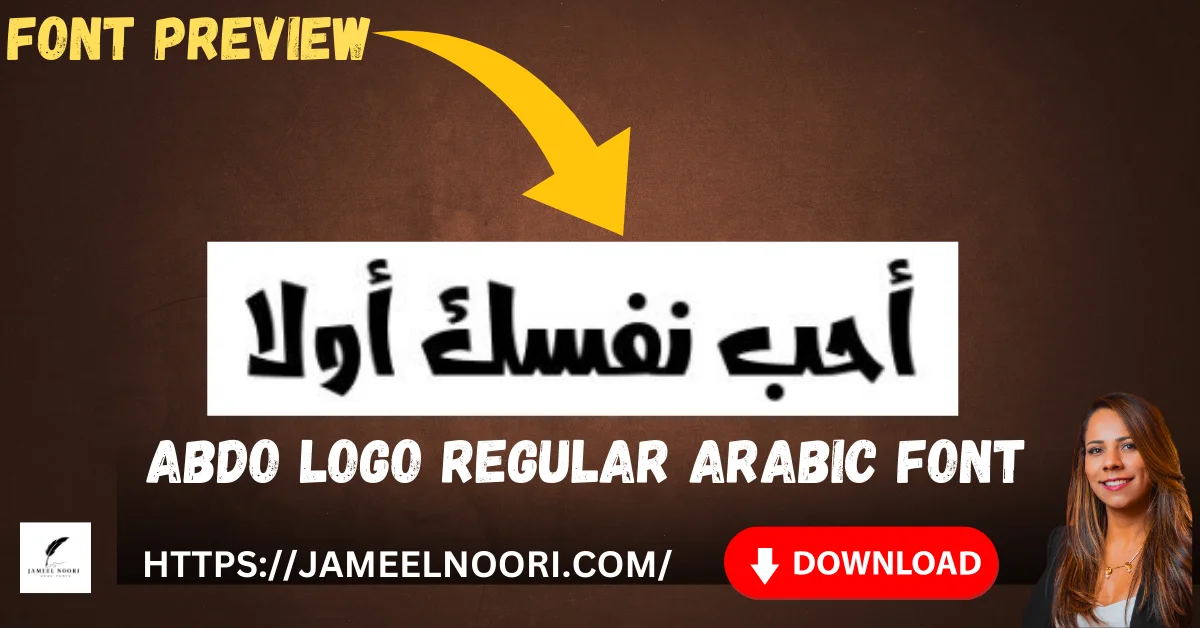
Abdo Logo Regular Arabic Font – Modern & Professional Arabic Typeface For Designers (Best & Latest Choice)
Abdo Logo Regular Arabic Font aik modern aur professional Arabic typeface hai jo specially logo design, branding, aur creative projects ke liye use hota hai. Ye font worldwide designers ke darmiyan bohat popular hai kyun ke iski clean calligraphy aur balanced letter spacing har design ko premium look deti hai. Is article me hum apko is font ke bare me complete information dy gy taki aap bina time waste kiye is font ka best use kar saken.
Key Features of Abdo Logo Regular Arabic Font
Abdo Logo Regular Arabic Font ke kuch powerful features isay market ka best arabic font banate hain:
• Clean aur modern Arabic calligraphy
• Logo aur branding ke liye perfect
• High readability on screen aur print
What Is Abdo Logo Regular Arabic Font and Why It Is the Best Choice
Is font ka structure simple magar classy hai, jo Urdu fonts aur Arabic fonts ke users dono ke liye easy readability provide karta hai. Lahore, Karachi aur dusray shehron ke designers isay logos, posters aur digital branding me frequently use karte hain.
Best Uses of Abdo Logo Regular Arabic Font Worldwide
Abdo Logo Regular Arabic Font multiple creative fields me use hota hai, jaise:
• Logo design & branding
• Social media graphics
• Website headers
• Posters & banners
• Islamic content & calligraphy
Pakistan ke ilawa Middle East aur Europe ke designers bhi isay commercial projects me confidently use karte hain.
Abdo Logo Regular Arabic Font character map and calligraphy details
Detailed character map of Abdo Logo Regular Arabic Font showing Arabic letters and design consistency.
Character Map and Calligraphy Style of Abdo Logo Regular Arabic Font
Abdo Logo Regular Arabic TTF Font ka Character Map section bohat helpful hai kyun ke yahan se aap har letter ki calligraphy samajh sakte hain. Iska letter flow smooth hai aur curves balanced hain jo logos ko strong visual identity dete hain.
Is font ka style Arabic fonts ke traditional touch ko modern typography ke sath merge karta hai. Isi wajah se ye font Urdu fonts ke users ke liye bhi appealing hai.
Comparison Table: Abdo Logo Regular Font vs Other Arabic Fonts
FeatureAbdo Logo RegularOther Arabic Fonts
ReadabilityHighMedium
Logo FriendlyYesLimited
User Rating4.6/53.8/5
TrueType SupportYesNot Always
Global UsageWorldwideRegional
Ye table clearly show karta hai ke Abdo Logo Regular Arabic Font ek ultimate aur expert choice hai.
Why Designers Prefer Abdo Logo Regular TTF Arabic Font in Pakistan
Abdo Logo Regular Arabic Font Pakistan ke designers ke liye affordable aur professional option hai. Lahore aur Karachi ke branding agencies is font ko is liye prefer karti hain kyun ke ye logo ko strong identity deta hai aur client expectations ko meet karta hai.
Iska lightweight structure web aur print dono ke liye suitable hai, jo isay long-term use ke liye reliable banata hai.
Abdo Logo Regular Arabic Font ek complete guide ke mutabiq dekha jaye to designers ke liye best, latest aur reliable option hai. Iski popularity, high rating aur professional look isay branding aur creative projects ke liye perfect banate hain. Agar aap aik aisa arabic font chahte hain jo modern ho, readable ho aur worldwide trusted ho, to ye font definitely try karna chahiye.
What makes this font different from other Arabic fonts?
Its clean calligraphy, logo-friendly design, and high readability set it apart.
Is Abdo Logo Regular True Type Arabic Font good for web design?
Yes, it provides excellent on-screen readability for websites.